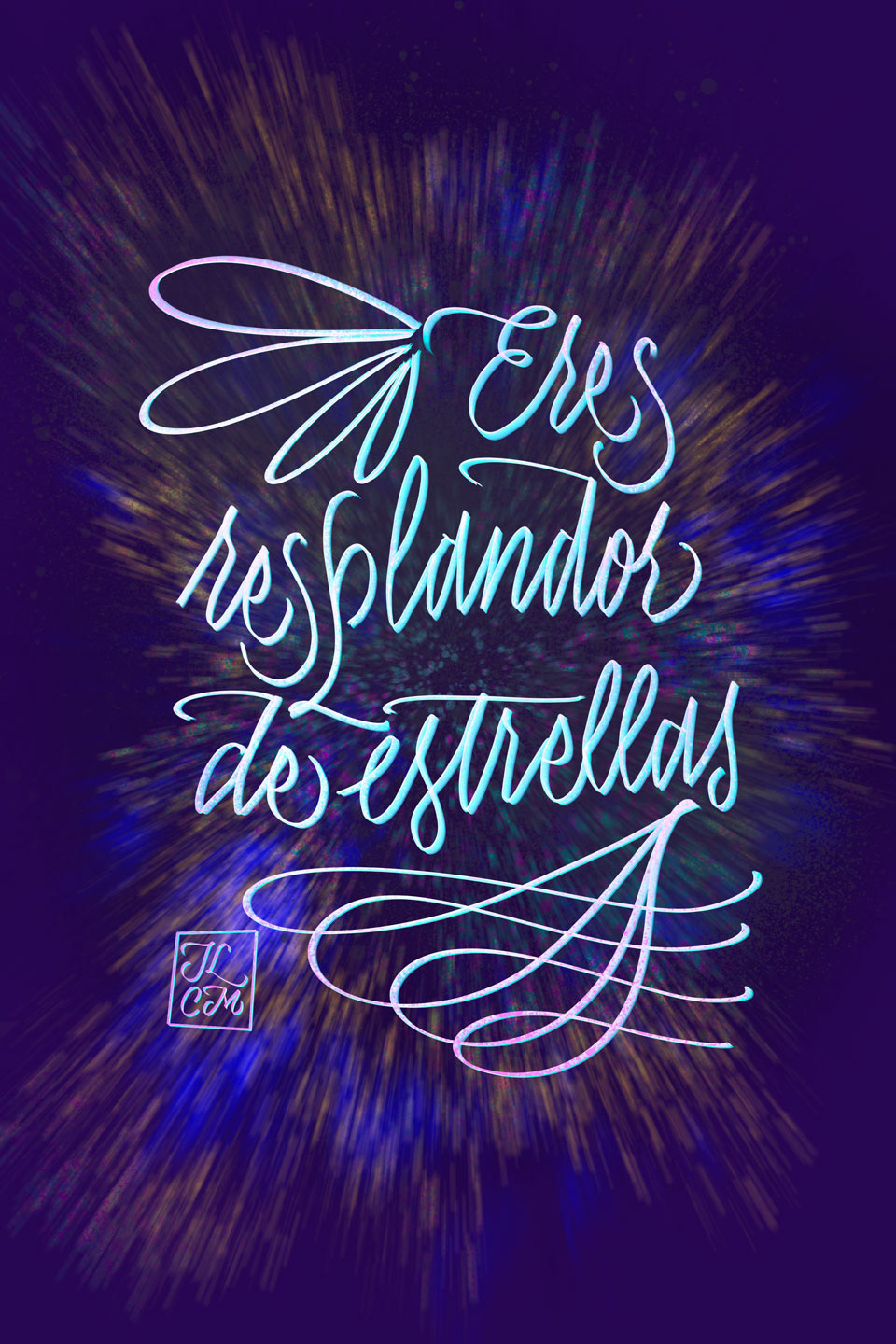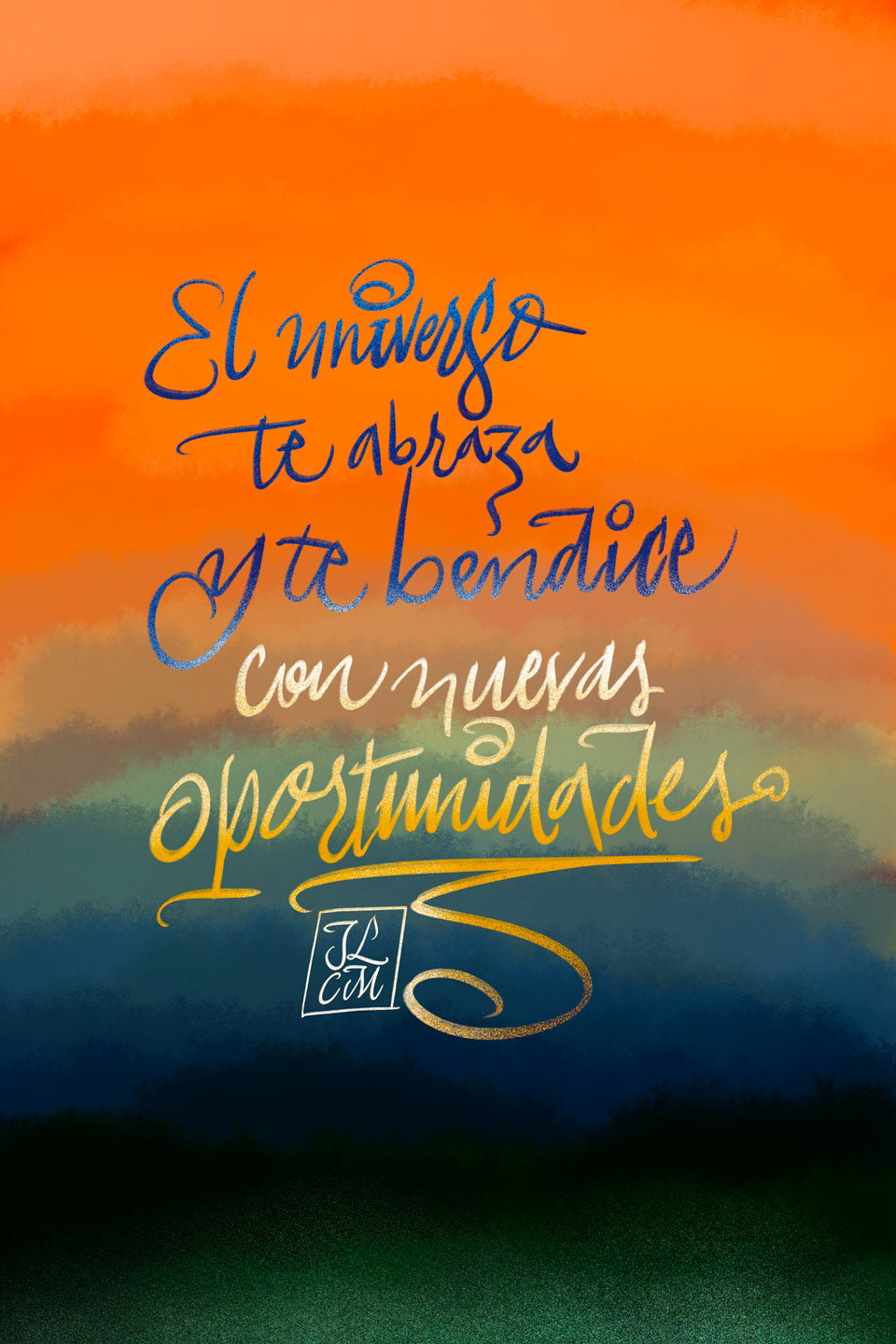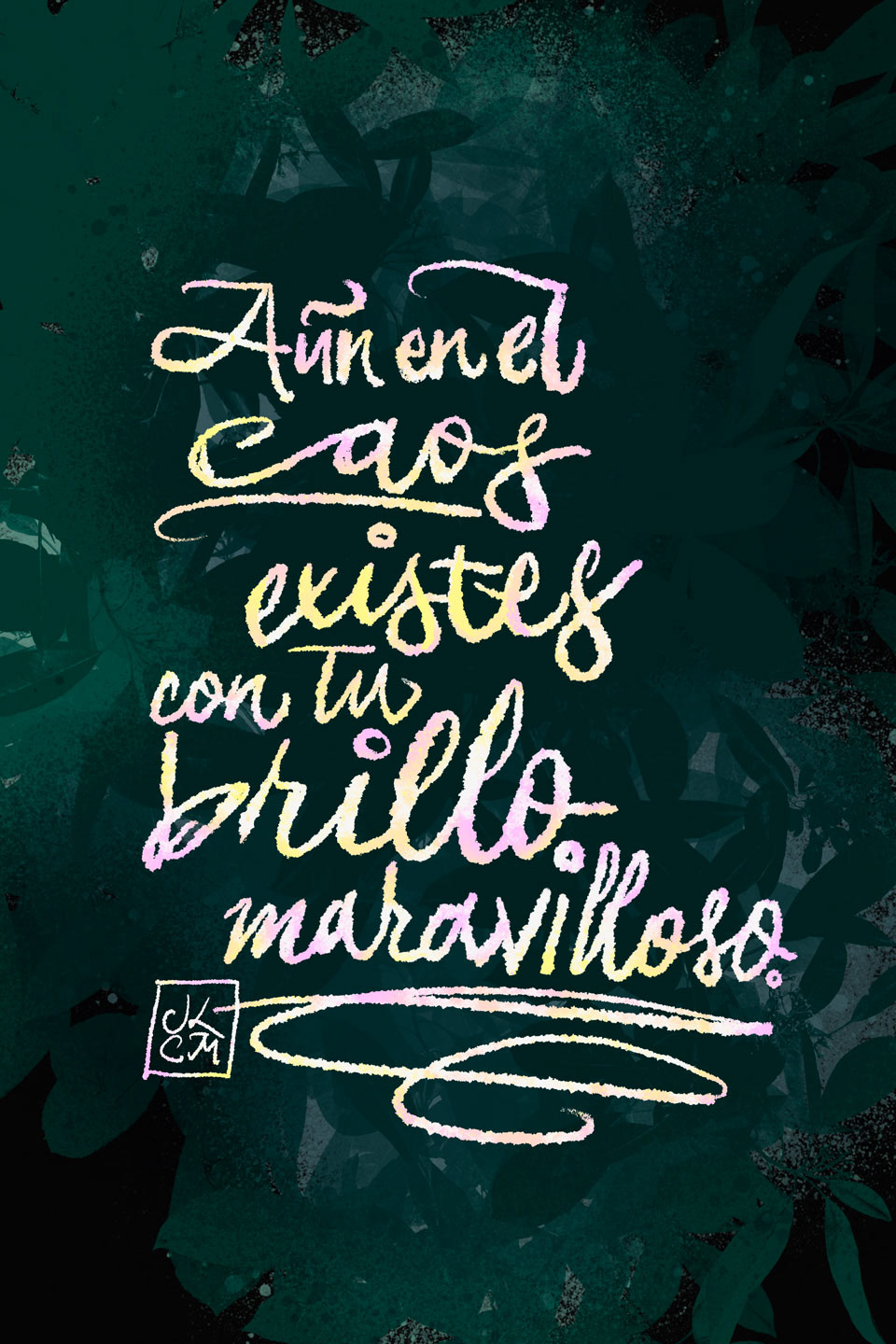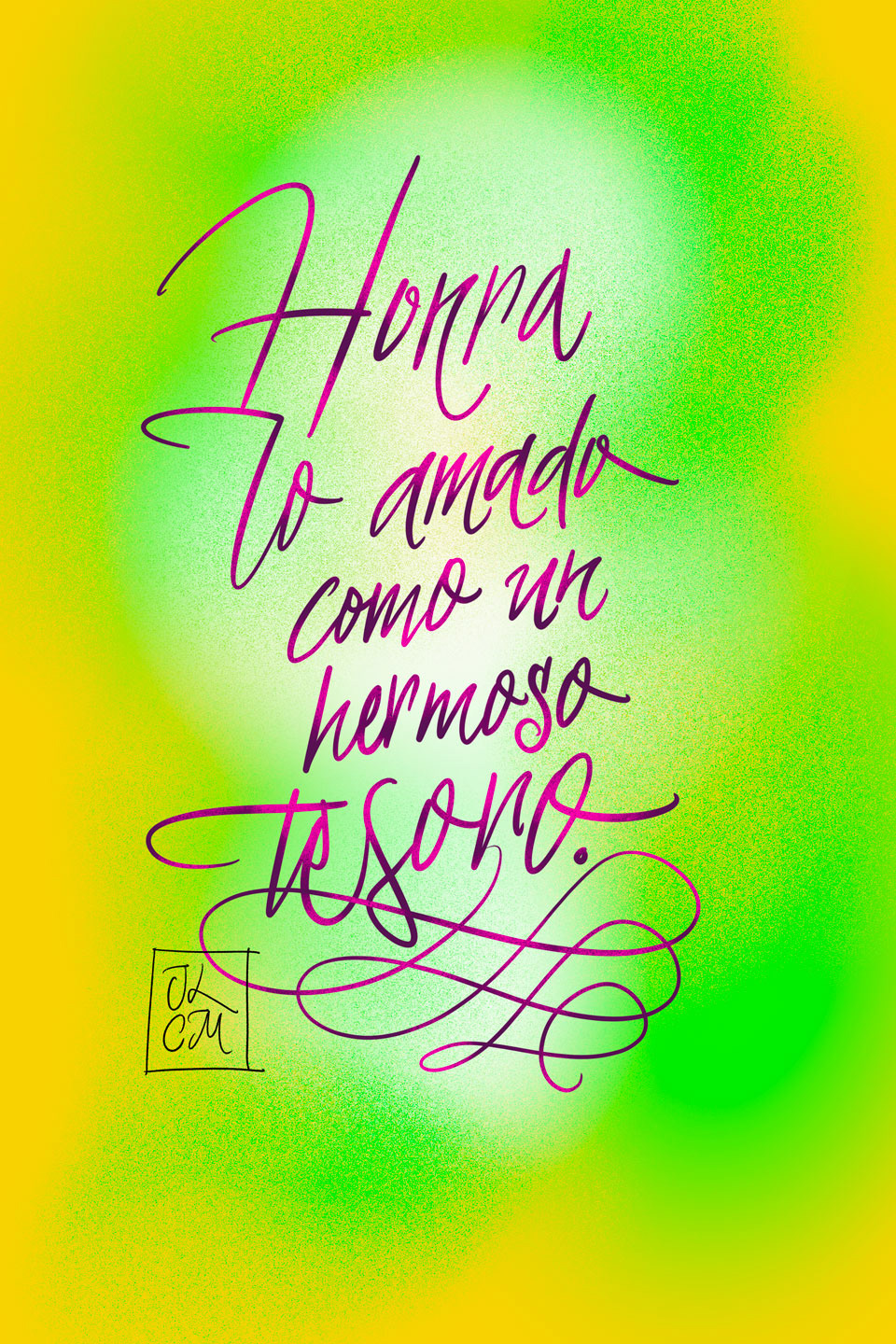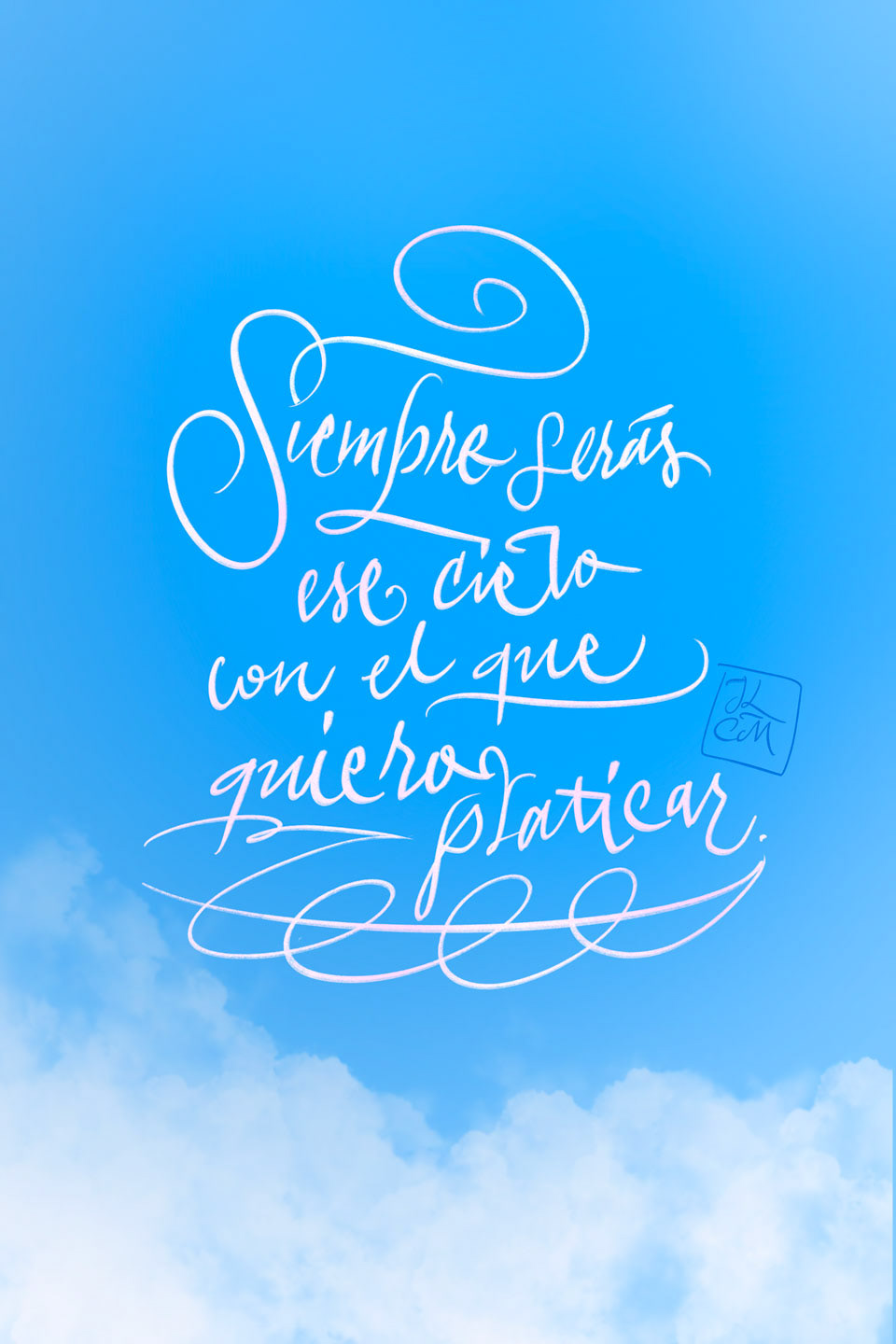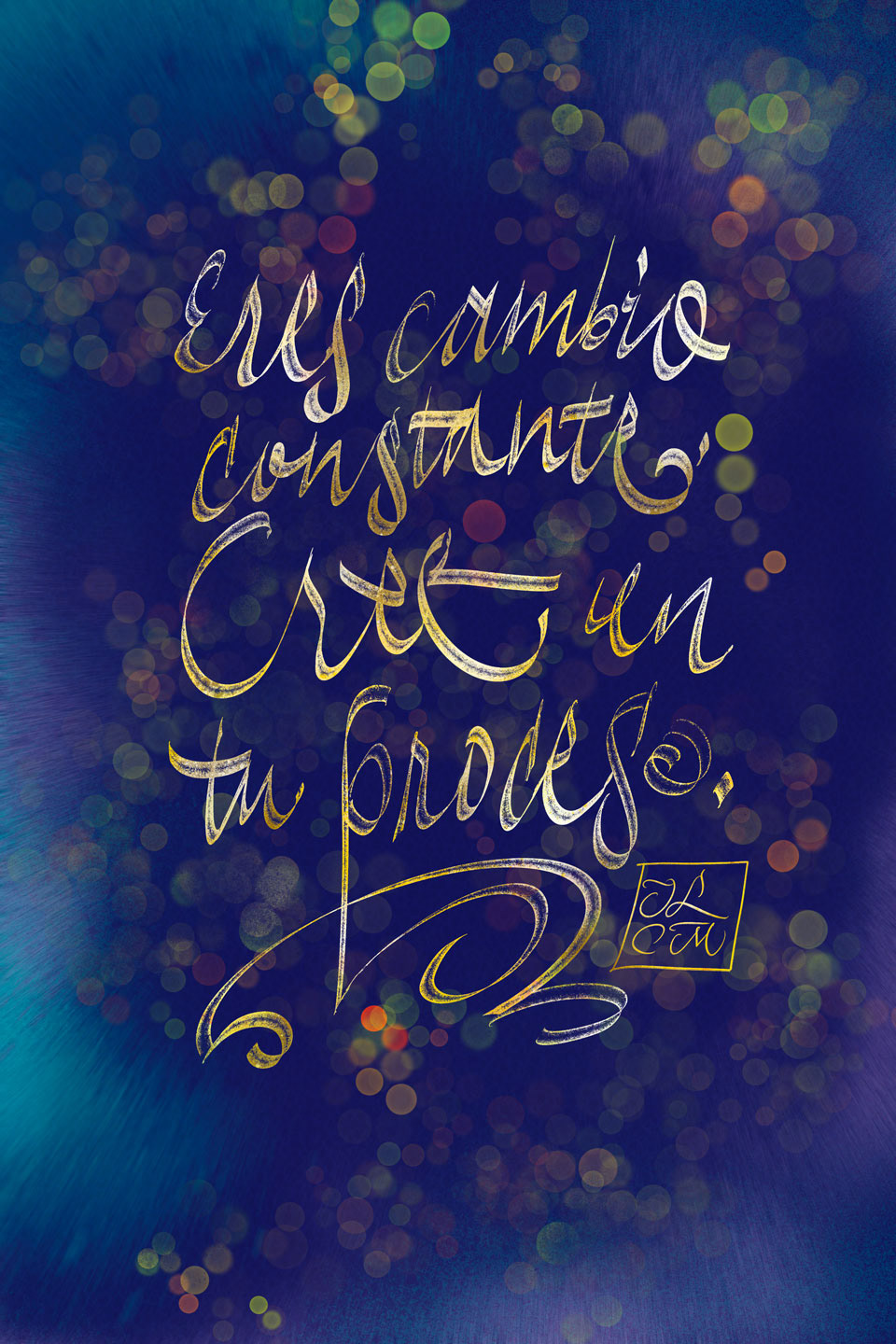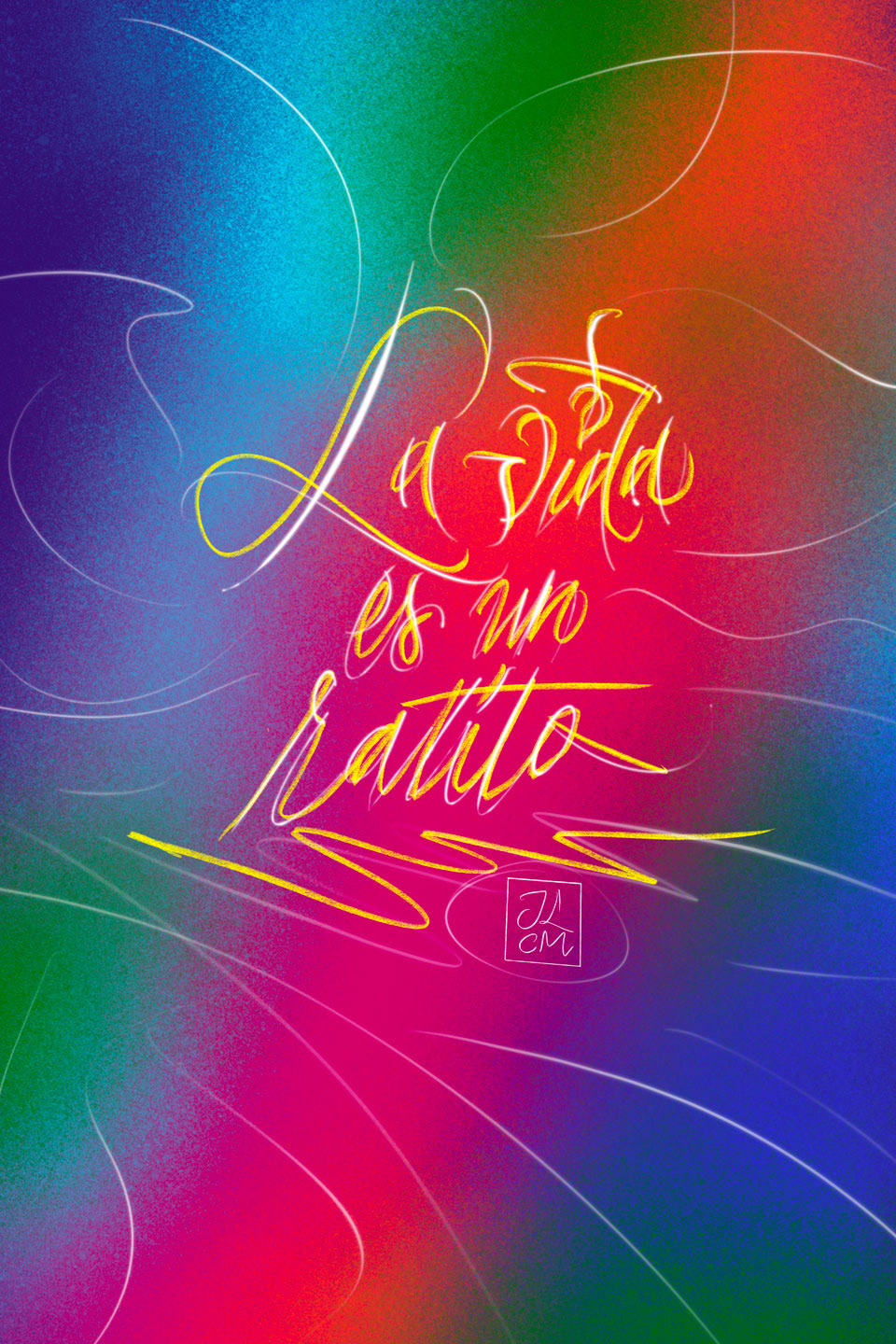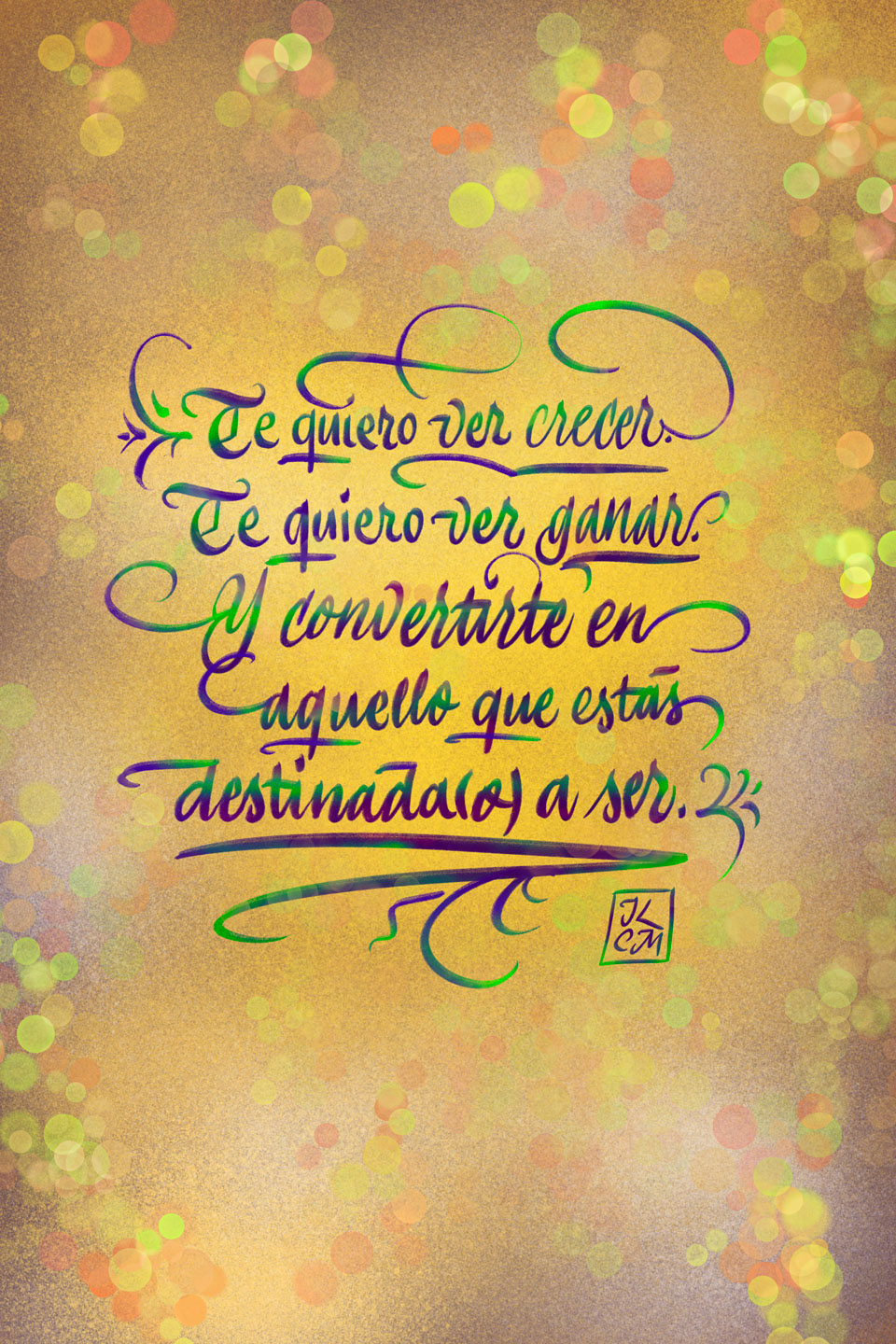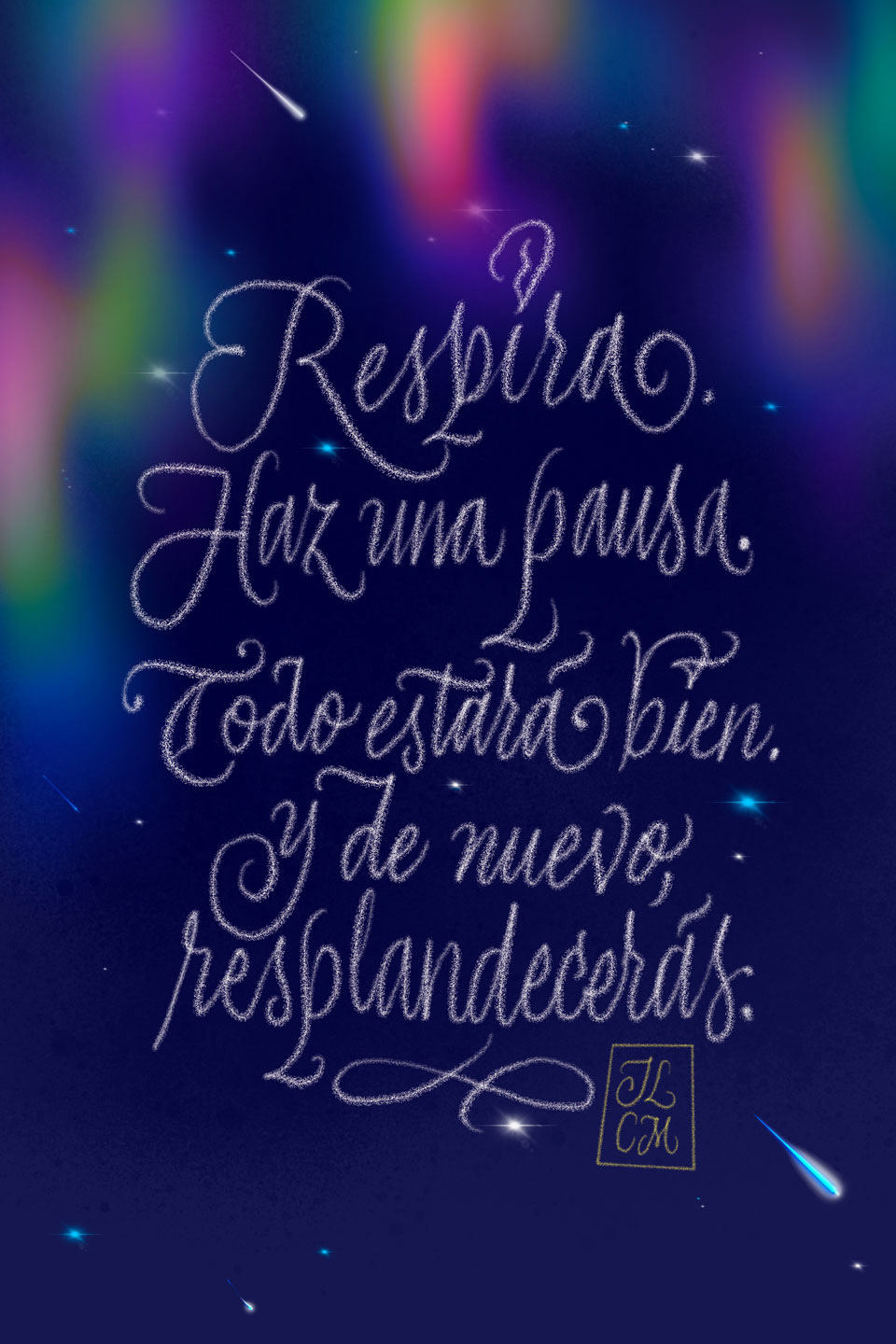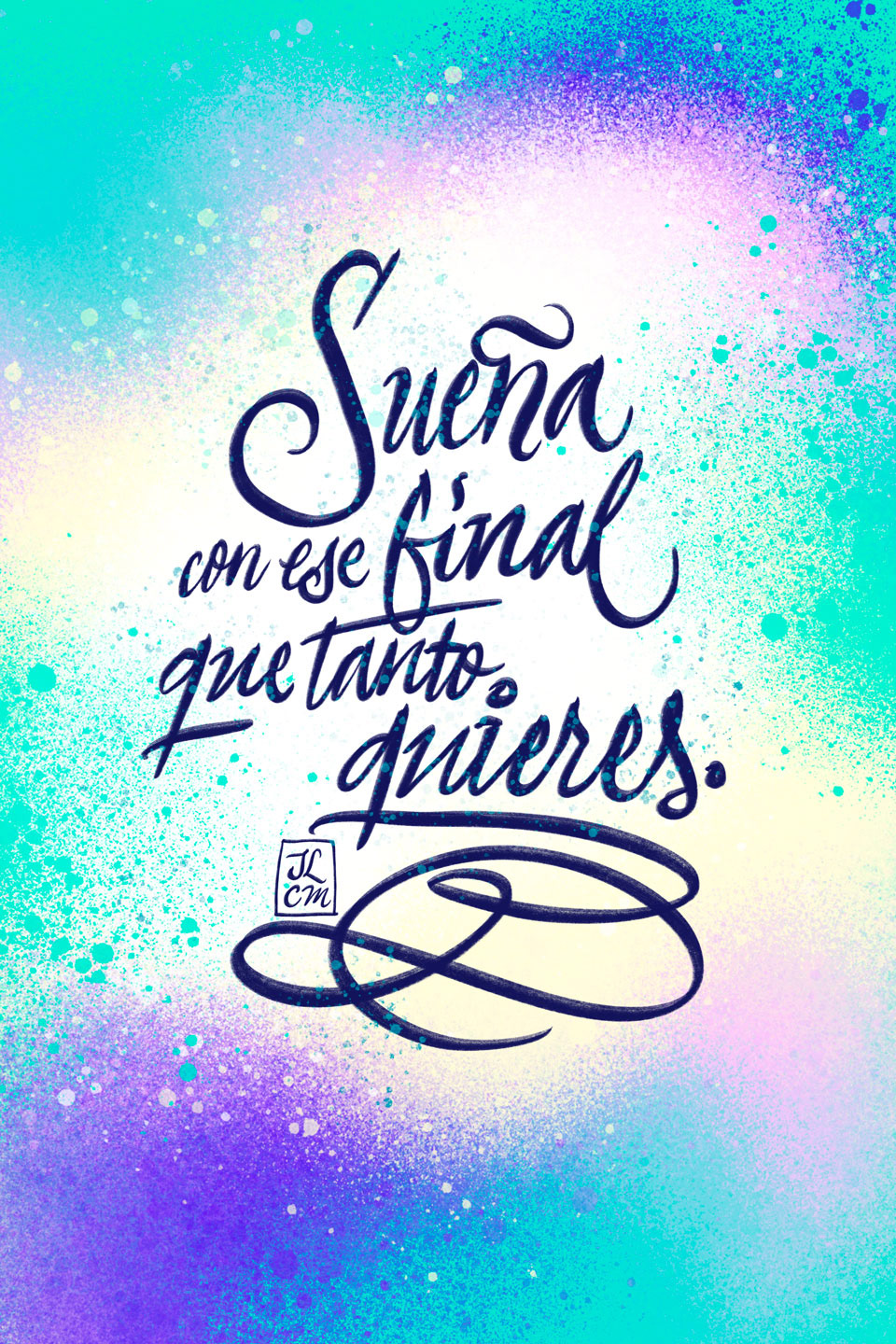
EL SOL CAMINA CONMIGO 5
Quinta temporada de "El Sol Camina Conmigo", un proyecto de postales digitales e historias para redes sociales con breves reflexiones cuidadosamente estilizadas con tipografía, texturas y colores vibrantes. Esta colección combina composiciones de lettering realizadas con Procreate en iPad y hermosos fondos creados con la misma aplicación.